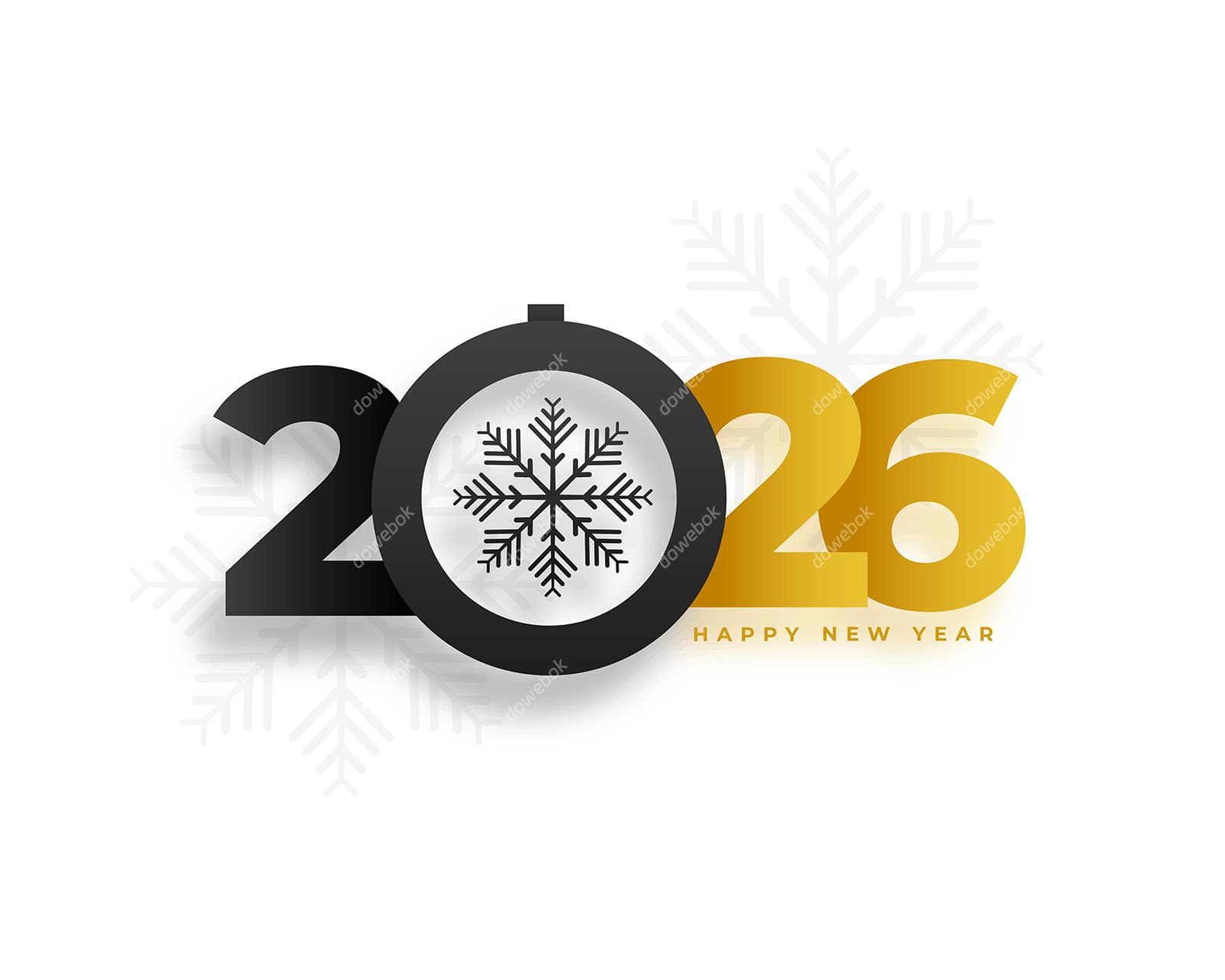
这是一款雪花和数字设计的 2026 新年快乐矢量素材,纯白背景简洁清爽,“2026” 以黑、金双色呈现,数字 “0” 化作嵌着雪花纹的黑色圆环,背景淡描雪花元素,呼应冬日氛围。下方 “Happy New Year” 字样简约点缀,整体以黑、金、白配色融合冬日符号,既显跨年的极简格调,又用雪花细节透出清冷雅致的节日质感,简洁却富有氛围感。